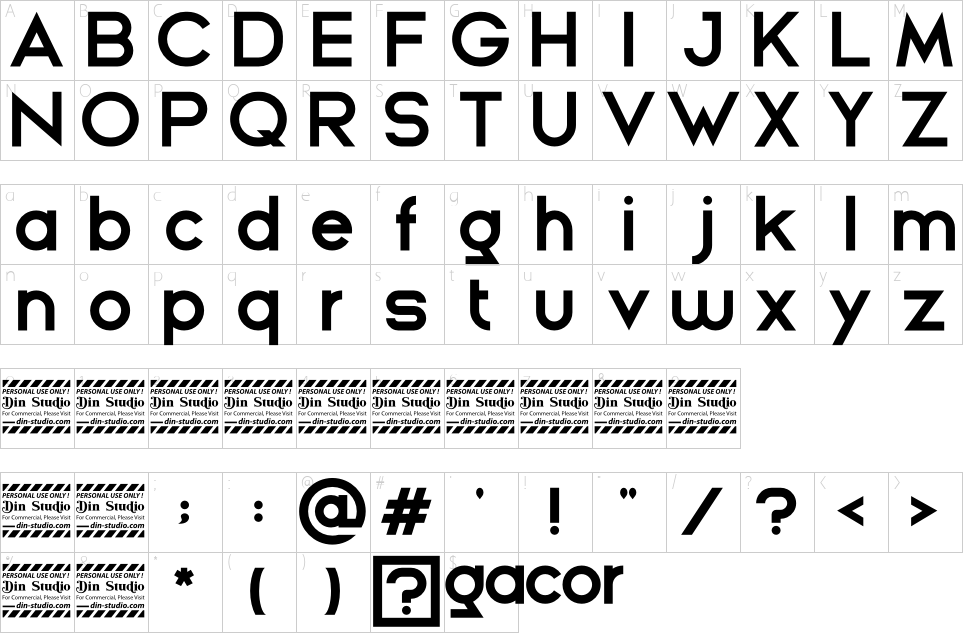
Aqui está uma descrição envolvente e natural para a página de download da font ‘gacor Font’, mantendo os requisitos: A gacor Font é uma elegante opção para designers digitais que buscam uma face moderna e fluida sem grandes compromissos. Desenhada pelo Din Studio, esta fonte ofertada gratuitamente se destaca por sua facilidade de uso e simplicidade. Com um design limpo e intuitivo, a gacor Font é perfeita para criar texturas sofisticadas em projetos gráficos digitais. Além disso, a gacor Font foi popularmente baixada 7.121 vezes, sugerindo que muitos profissionais já se beneficiaram da sua beleza e funcionalidade. Se você está buscando uma fonte de graça para seus projetos, sem comprometer na qualidade visual, a gacor Font é um excelente escolha. Combinada com outros recursos gratuitos disponíveis no mercado, ela pode transformar seu trabalho em algo realmente único e profissional.